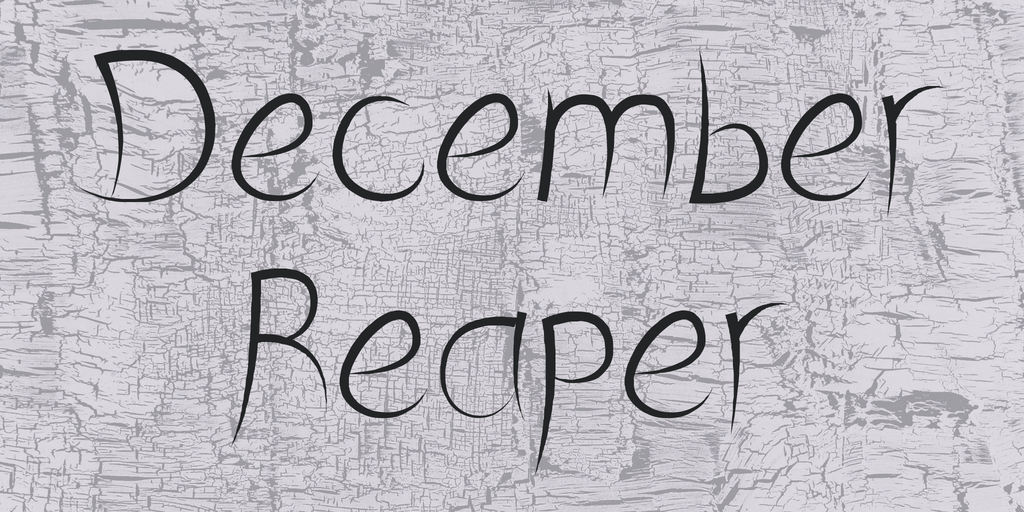
A fonte “December Reaper” é uma elegante fonte sans-serif criada pelo designer Hamilton. Com um design limpo e moderno, ela se destaca para uso tanto em projetos pessoais quanto profissionais. Esta fonte foi desenvolvida com habilidades de tipografia avançadas, proporcionando-lhe uma ampla gama de opções estilísticas que vão do minimalismo ao elegante. Para o uso comercial, Hamilton está disponível para contato direto se você desejar incorporá-la em seus trabalhos comerciais. Se você adora esta fonte, é uma ótima ideia encontrá-lo no Facebook.com/llott6designs para manter-se atualizado com seus outros projetos e criações. A “December Reaper” oferece um toque único que pode transformar qualquer projeto em algo especial e único.